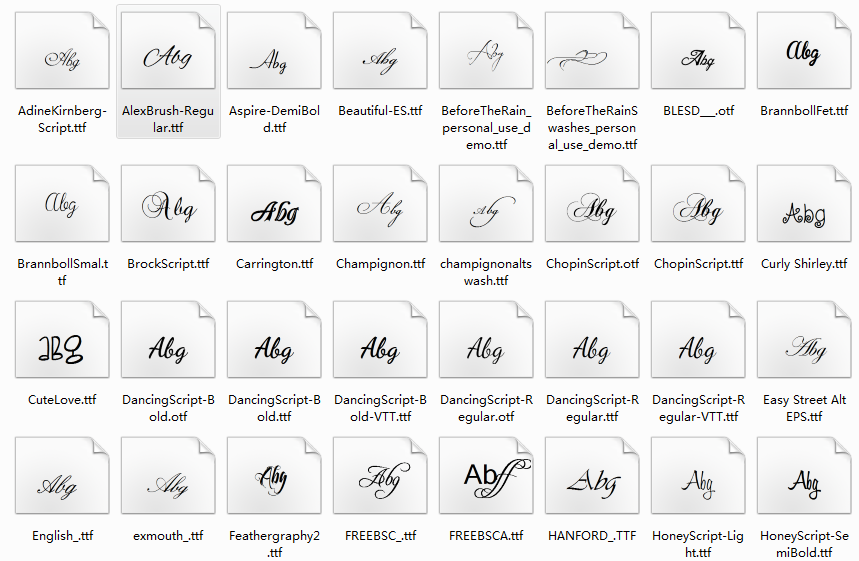
婚禮幸福英文字體是一款非常精美的字體,小編為大家整理了42款,用途非常的廣泛,字體本身就充滿了濃濃的幸福和浪漫的氣息,配合使用logo的設(shè)計(jì)、請(qǐng)柬、賀卡都是不錯(cuò)的選擇,喜愛的朋友趕快下載體驗(yàn)吧!
在婚禮網(wǎng)站或是一些珠寶、服飾類網(wǎng)站中,我們經(jīng)常會(huì)用一些比較漂亮的的字體來提升網(wǎng)站視覺效果,一些優(yōu)雅的字體,除了網(wǎng)站上使用外,還能用于制作一些精美的賀卡、邀請(qǐng)函、婚禮請(qǐng)柬等等。